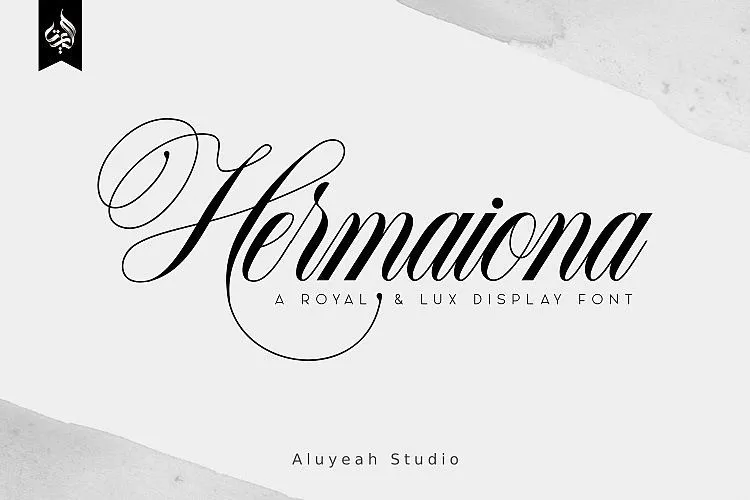
Descubra a Hermaiona Script Font, uma elegante e sofisticada tipografia moderna para qualquer projeto que valorize luxo e exclusividade. Desenvolvida por 24Design, esta fonte script é perfeita para criar textos de alta qualidade em design de moda, beleza, eventos especiais ou mesmo publicações online. Com cada letra cuidadosamente criada, a Hermaiona Script transmite um ar de elegância e riqueza que se adequa perfeitamente à sua necessidade de estilos luxuosos para marcas de alta qualidade. Ideal tanto para identidades visuais complexas quanto para aplicativos digitais como anúncios e cabeçalhos, esta fonte é uma escolha ótima para quem busca transmitir sofisticação em cada projeto. Seja para criar um branding impecável ou adicionar uma atmosfera de luxo em sua próxima publicação, a Hermaiona Script proporcionará o resultado perfeito que você está procurando.